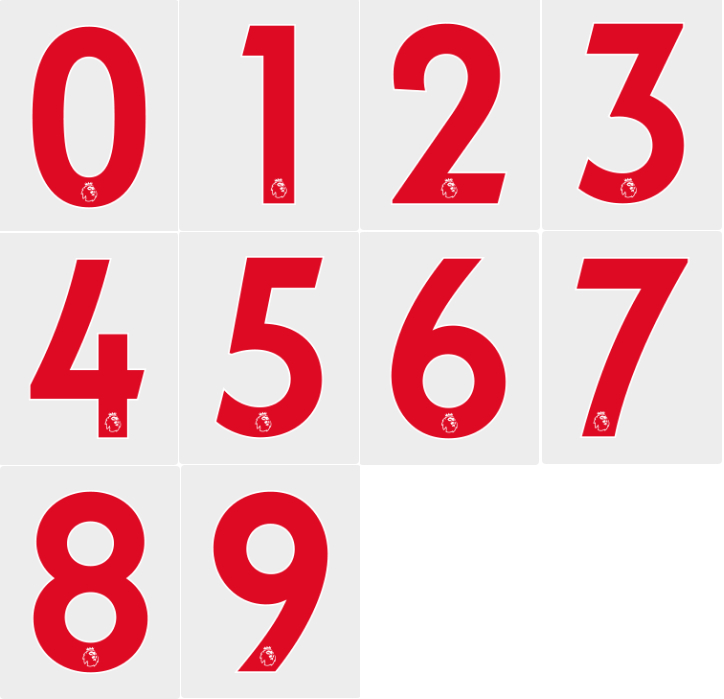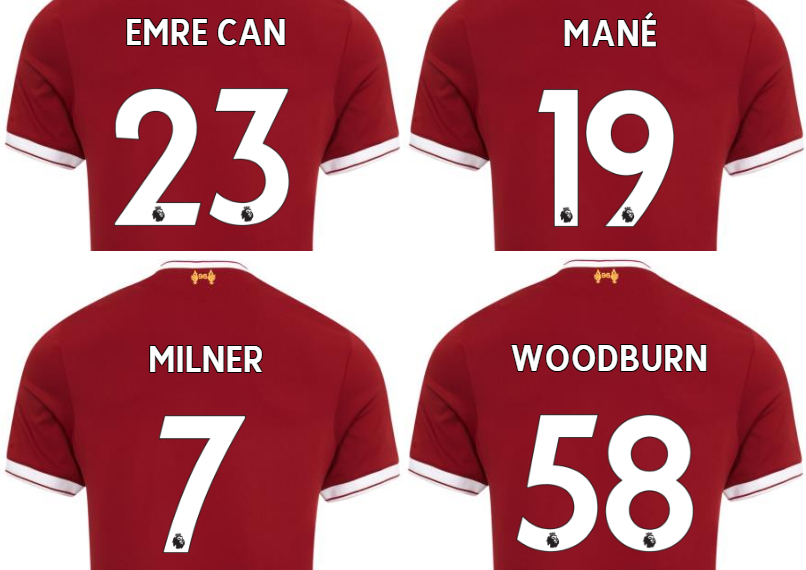
今季、リーグロゴのデザインをリニューアルしたプレミアリーグ。当初は背番号とユニフォームフォントも合わせて一新する予定だったが、それは来季に持ち越しになったとされていた。
そんななか、プレミアリーグのオフィシャルパートナーである『Sporting iD』が新たなフォントを公開していた。
色の組み合わせは「白×黒」「黒×白」「紺×白」「赤×白」「黄×白」の5つだとされている。「赤×白」はこんな感じ。
2017-18 Premier League Fonts
今季までのフォントと比べると、その違いが分かる。
また、2017-18シーズンに向けた新ユニフォームを発表したリヴァプールのHPでも、新フォントと新ユニネームを確認することができる。
評価が高かったこれまでのフォントと比べると、クセがなくなった感じだろうか。